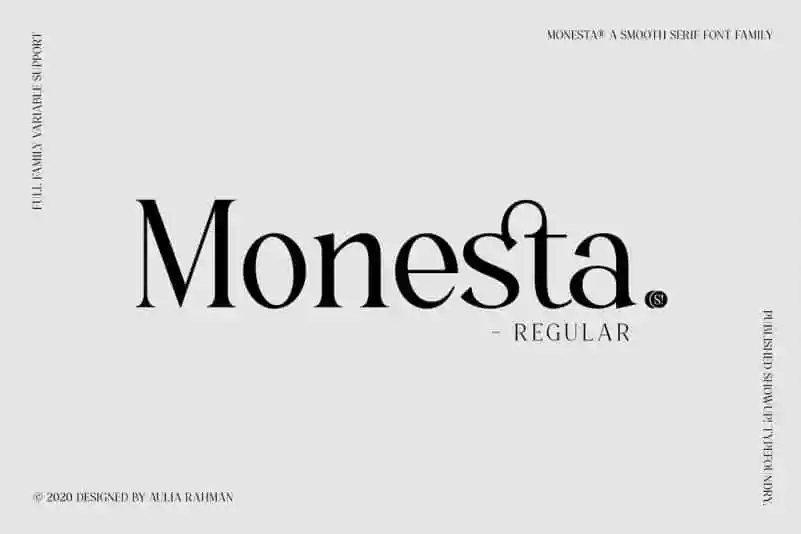
Monesta Serif é uma fonte serif que traz um estilo único de ligatura, criada pela Aulia Rahman através do site 99designs. Este design moderno e sofisticado oferece um tom suave e expressivo, ideal para textos importantes em suas aplicações. O conceito da Monesta® se concentra no direcionamento para a usabilidade, permitindo que ela atue tanto como uma ferramenta de estilo bold quanto como uma comunicadora bela. Este é um recurso de qualidade para designers e criativos buscando dar vida aos seus projetos com um toque elegante e sofisticado.